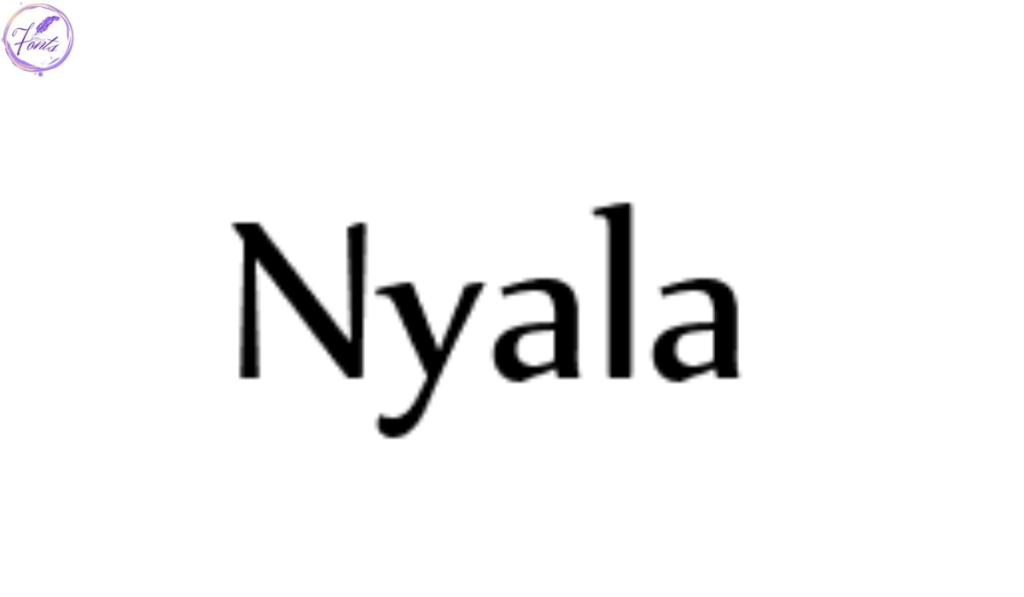
Nyala font việt hóa
Tác giả: John Hudson và Geraldine Wade
Ngày phát hành: 2003
Ngôn ngữ: Amharic, Tiếng Việt, Tiếng Anh, và nhiều ngôn ngữ khác
Bộ Font: Nyala
Phân loại: Cá tính, độc đáo
Kiểu chữ: Kiểu chữ có chân
Độ dày: Nyala Regular
Nyala font là một font chữ độc đáo, lấy cảm hứng từ văn hóa và ngôn ngữ Ethiopia. Được thiết kế bởi John Hudson và Geraldine Wade, phát hành vào năm 2003, font Nyala nổi bật với các đường nét mềm mại và uyển chuyển. Font này mang đến một vẻ đẹp tinh tế và truyền thống, rất phù hợp cho các dự án thiết kế liên quan đến văn hóa và lịch sử. Với sự hỗ trợ đầy đủ các ký tự tiếng Việt, nyala font giúp các nhà thiết kế dễ dàng tạo ra các tác phẩm độc đáo và sáng tạo.
Đánh giá nyala font
Nyala font được đánh giá cao bởi sự pha trộn hoàn hảo giữa nét truyền thống và hiện đại. Người dùng yêu thích font này vì nó mang lại cảm giác thanh lịch và dễ đọc, dù ở kích thước nhỏ hay lớn. Ngoài ra, nyala font còn hỗ trợ đa ngôn ngữ, giúp tăng tính linh hoạt trong các dự án thiết kế quốc tế. Với tính thẩm mỹ cao và tính ứng dụng đa dạng, nyala font là một công cụ đắc lực cho các nhà thiết kế muốn tạo dấu ấn riêng và ấn tượng.